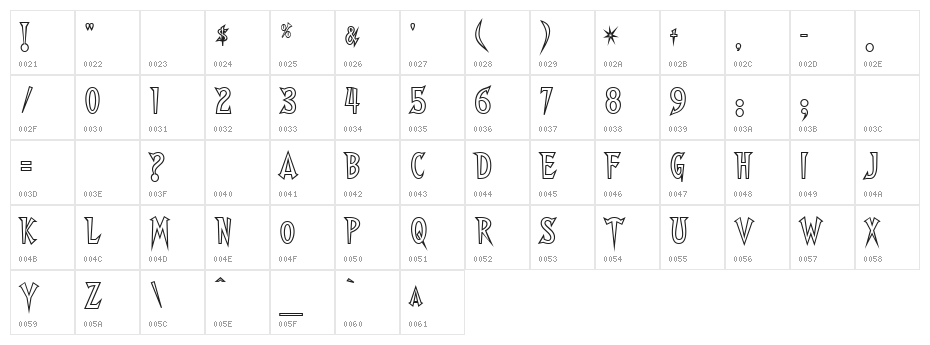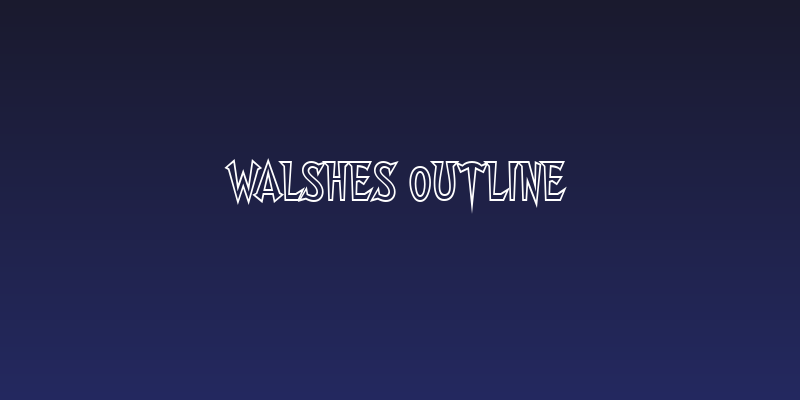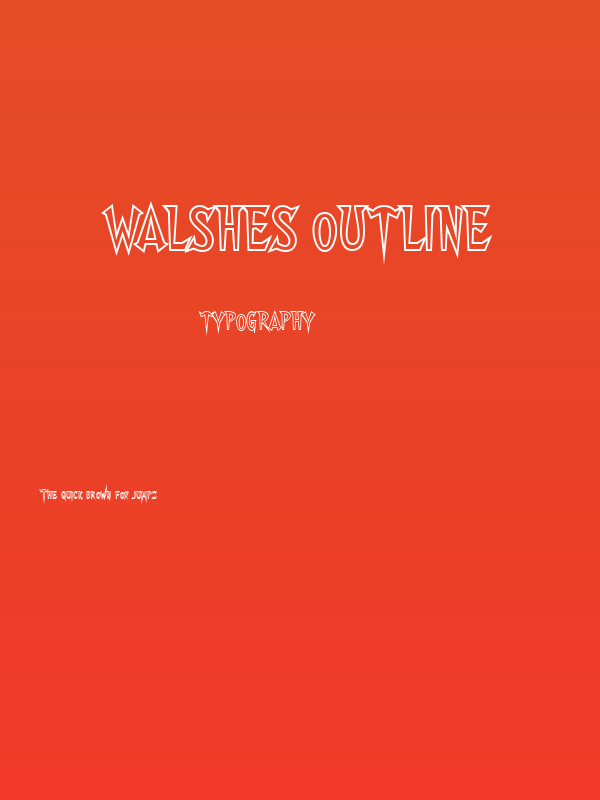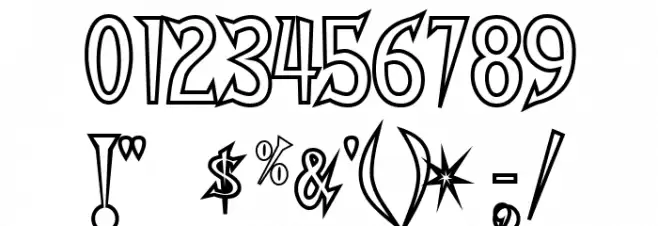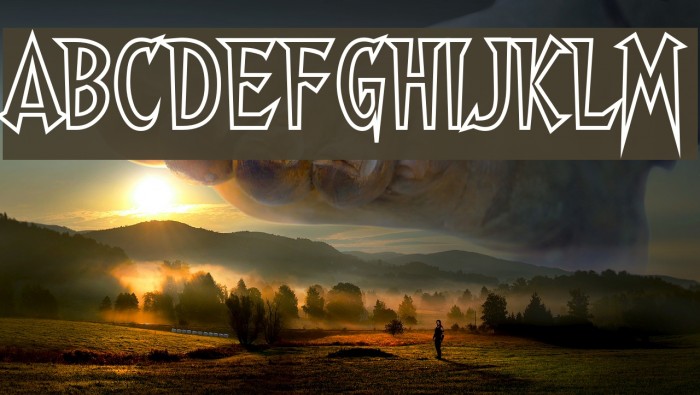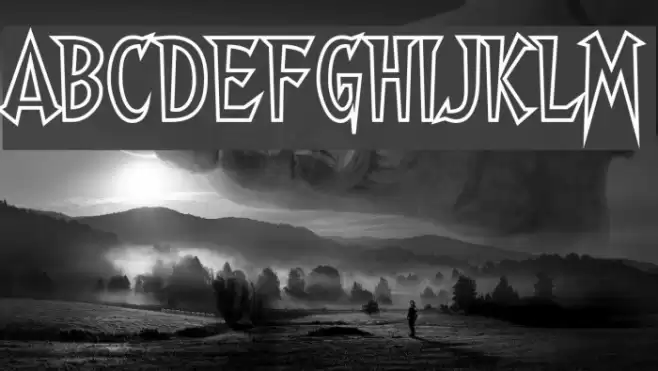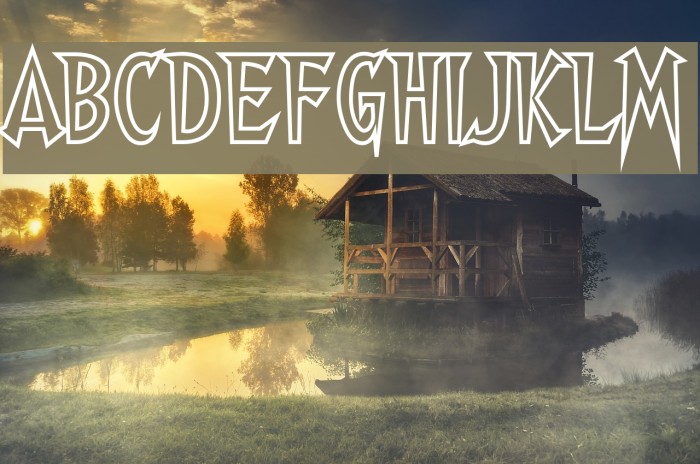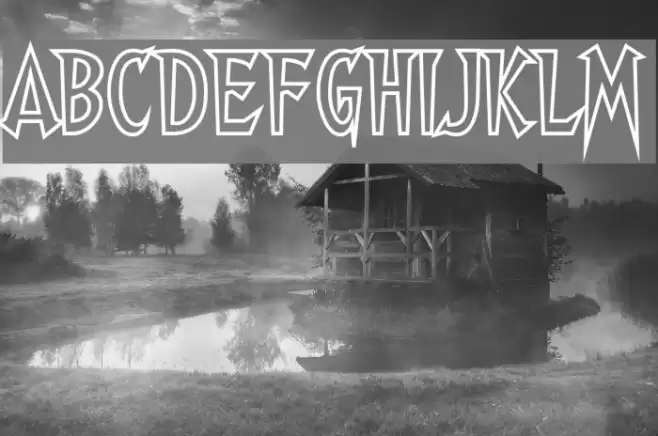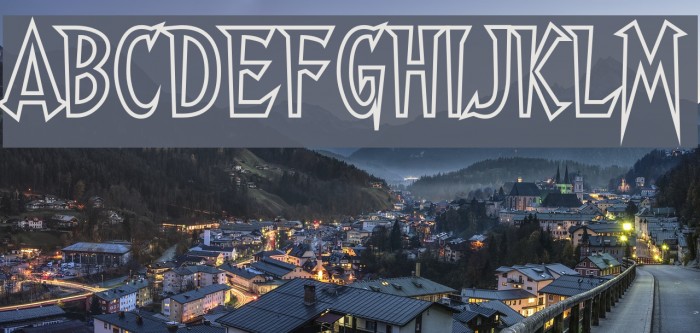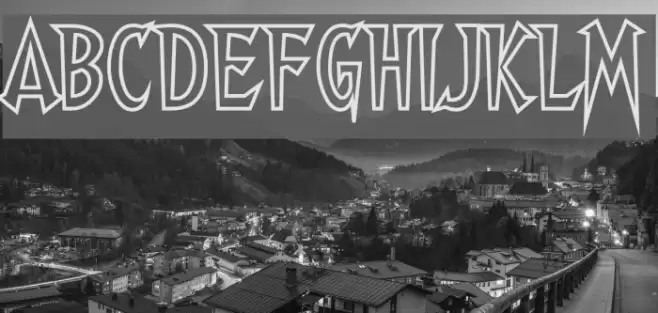
Walshes Outline Font
| Stile generale | Modern, Edgy |
| Progetti proposti | Ideal for posters, album covers, branding for edgy or modern products, and any design needing a bold statement. |